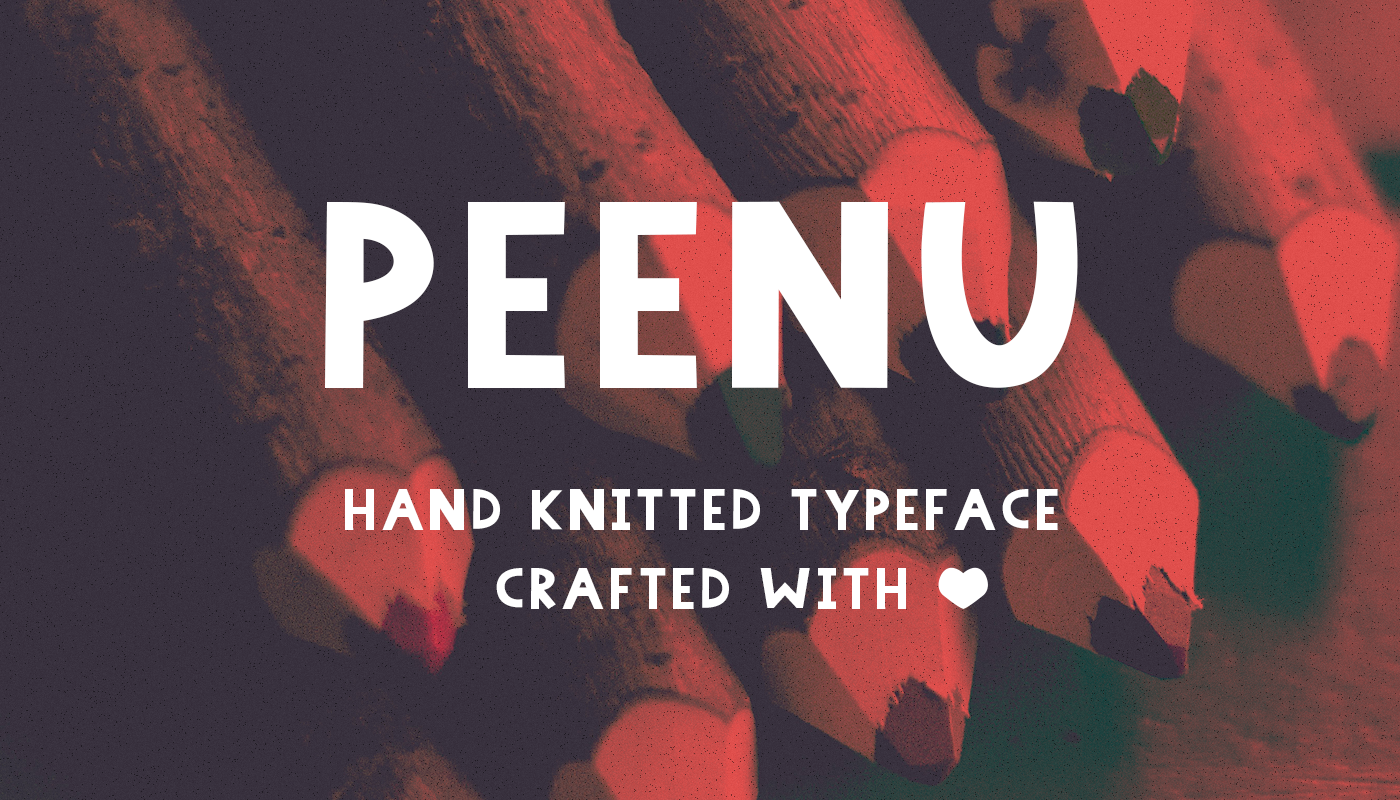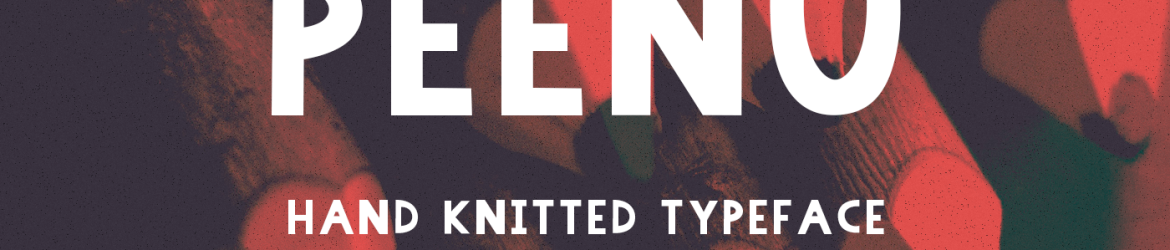
Peenu é uma nova fonte sans-serif criada pelo designer Hamilton, inspirada na arte do corte delicado no papel, conhecido como paper cuts, e também inspirada nos crochets artesanais ou tricôs feitos à mão. Com essa fonte, você pode experimentar um toque suave e personalizado em seus projetos de design, sem a necessidade de atribuição formal. Inspirado no charme único e delicado dos corte de papel e do crochê, Peenu oferece uma abordagem única para os designs que procura algo além daquilo que é comum. Perfecta para criar um estilo distintivo em elementos digitais ou impressos, a fonte Peenu é como um pedacinho de arte na tela de sua próxima criação gráfica.